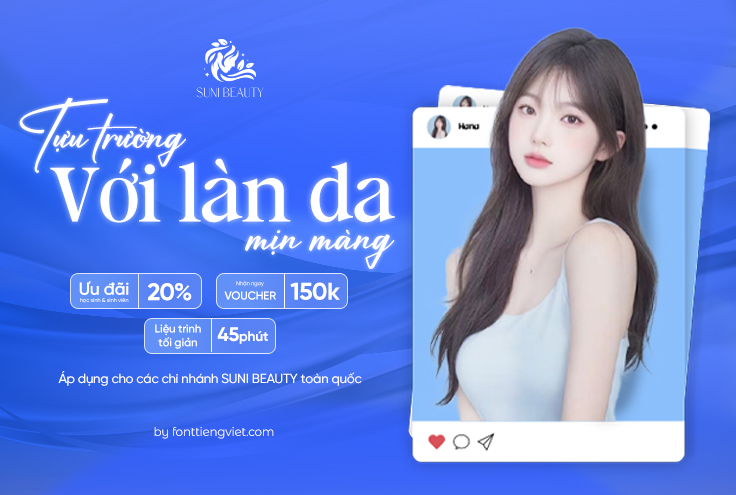
Combo font thiết kế Spa – Làm đẹp – Mỹ phẩm
Combo font thiết kế Spa – Làm đẹp – Mỹ phẩm: Bí quyết nâng tầm thương hiệu chuyên nghiệp
Khám phá bộ Combo font thiết kế Spa – Làm đẹp – Mỹ phẩm chuyên dụng
Trong ngành công nghiệp thẩm mỹ và chăm sóc sắc đẹp, diện mạo thị giác đóng vai trò quyết định đến niềm tin của khách hàng. Việc lựa chọn một Combo font thiết kế Spa – Làm đẹp – Mỹ phẩm phù hợp không chỉ giúp truyền tải thông điệp thương hiệu mà còn tạo nên cảm giác thư thái, sang trọng và tinh tế. Một thiết kế ấn tượng bắt đầu từ những Font Miễn Phí chất lượng, giúp các nhà thiết kế dễ dàng truyền tải sự mềm mại của các dịch vụ chăm sóc da hay sự đẳng cấp của dòng mỹ phẩm cao cấp. Bộ sưu tập này được tuyển chọn kỹ lưỡng để đáp ứng mọi nhu cầu từ logo, bao bì đến menu dịch vụ.
Tầm quan trọng của font chữ trong ngành làm đẹp
Ngành làm đẹp đòi hỏi sự tỉ mỉ và tính thẩm mỹ cao độ. Khi sử dụng bộ font chuyên biệt, bạn sẽ thấy sự khác biệt rõ rệt trong cách khách hàng cảm nhận về doanh nghiệp. Các kiểu chữ thanh mảnh thường gợi lên sự nhẹ nhàng, trong khi những font có chân (Serif) hiện đại lại mang đến vẻ quyền quý và uy tín. Việc kết hợp khéo léo các bộ font trong cùng một phong cách giúp bố cục thiết kế trở nên hài hòa, tránh sự lộn xộn và gây mất tập trung cho người xem.
Các đặc điểm nổi bật của Combo font thiết kế Spa – Làm đẹp – Mỹ phẩm
Bộ sưu tập này tập trung vào các phông chữ có tính ứng dụng cao, giúp tối ưu hóa thời gian thiết kế cho người dùng Việt. Điểm nhấn lớn nhất là sự đa dạng về kiểu dáng, từ phong cách tối giản (Minimalism) đến phong cách nghệ thuật bay bổng.
Font chữ Serif cho sự sang trọng và đẳng cấp
Các font chữ Serif luôn là lựa chọn hàng đầu cho các thương hiệu mỹ phẩm phân khúc cao cấp. Với những đường nét sắc sảo và phần chân chữ được gọt giũa tinh tế, chúng tạo nên một không gian chuyên nghiệp, đáng tin cậy. Đây là thành phần không thể thiếu trong bộ combo để làm nổi bật tên thương hiệu trên các bảng hiệu hoặc tiêu đề trang web lớn.
Font chữ Script và Handwriting cho sự mềm mại
Để tạo cảm giác gần gũi, thư giãn như đang ở trong một không gian Spa yên tĩnh, các font chữ viết tay (Handwriting) hoặc chữ nghệ thuật (Script) được tích hợp vào combo. Những đường cong uốn lượn mô phỏng nét chữ thủ công giúp thiết kế trở nên mềm mại, nữ tính và đầy cảm xúc, rất phù hợp cho các câu slogan hoặc thiệp mời sự kiện làm đẹp.
Cách ứng dụng hiệu quả Combo font thiết kế Spa – Làm đẹp – Mỹ phẩm
Sử dụng bộ font này đòi hỏi sự tinh tế trong việc phân bổ không gian và màu sắc. Thông thường, bạn nên sử dụng một font chữ đậm, rõ nét cho các tiêu đề chính và một font chữ không chân (Sans-serif) đơn giản cho phần nội dung mô tả chi tiết để đảm bảo tính dễ đọc. Sự tương phản giữa nét cứng cáp và nét mềm mại sẽ tạo nên một tổng thể thiết kế bắt mắt và hiện đại.
Tối ưu hóa thiết kế bao bì và bộ nhận diện
Bao bì sản phẩm mỹ phẩm là nơi font chữ tỏa sáng mạnh mẽ nhất. Với bộ combo này, bạn có thể dễ dàng thiết kế nhãn chai, hộp kem dưỡng hay các túi giấy đựng quà. Việc đồng bộ hóa font chữ trên tất cả các kênh từ Facebook, Instagram đến cửa hàng vật lý giúp tăng nhận diện thương hiệu một cách hiệu quả, tạo ấn tượng sâu sắc trong tâm trí khách hàng ngay từ cái nhìn đầu tiên.
Kết luận về bộ sưu tập font chữ làm đẹp